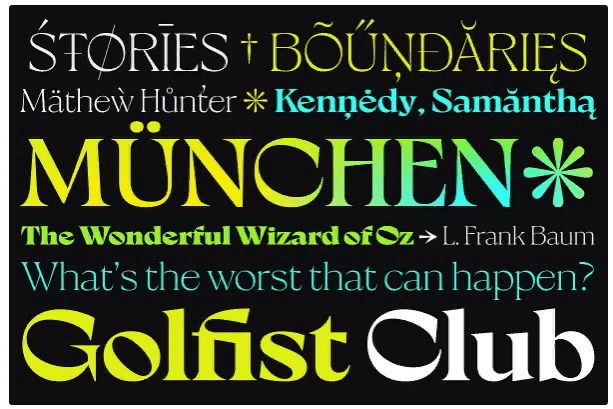
НОВЫЙ ШРИФТ MILANESA SERIF. Переменный шрифт включен. - Шрифты с засечками претерпевали постоянные изменения с течением времени; это позволило создать современные формы, которые придают выразительность каждой букве, делая их интересными в использовании и дизайне.
Milanesa Serif - это семейство шрифтов с семью весами, которое меняет угол контраста в своей черной версии, добиваясь особого перехода в различных интерполяциях. Не ограничиваясь традиционными канонами засечек, Milanesa играет с современной концепцией, чтобы продемонстрировать свою универсальность в различных графических приложениях.
Milanesa Serif претерпевает метаморфозы в своих весах, усиливая свои формы и варьируя свои контрформы без потери смысла семейства шрифтов, идеально подходящих для универсального использования, такого как веб-дизайн, редакция или упаковка, среди многих других.